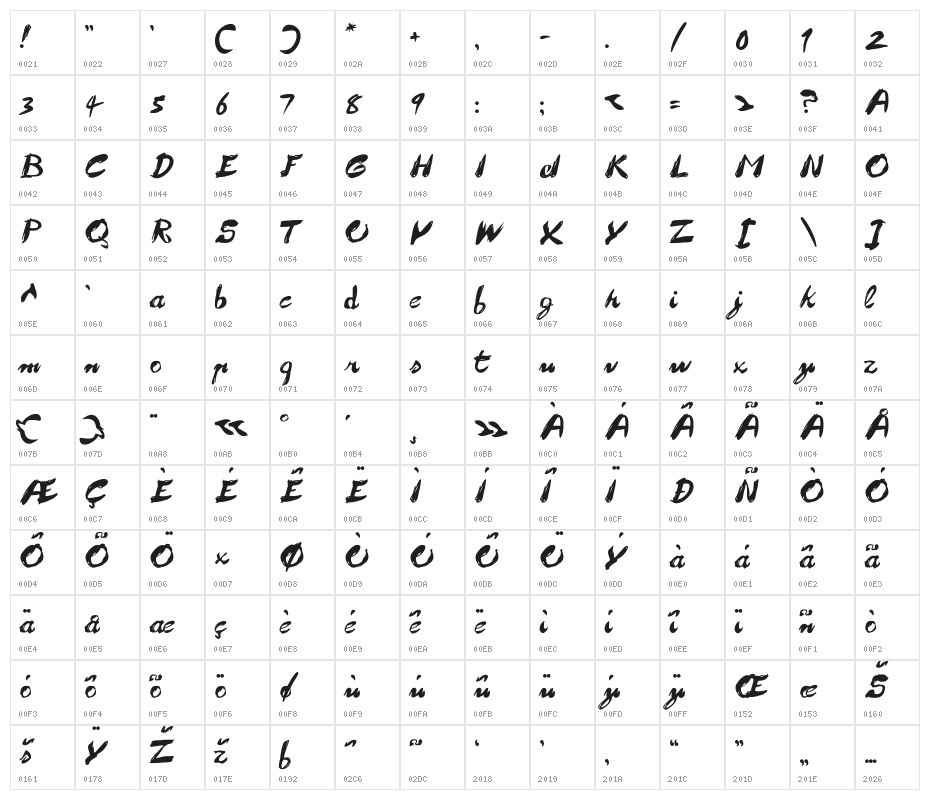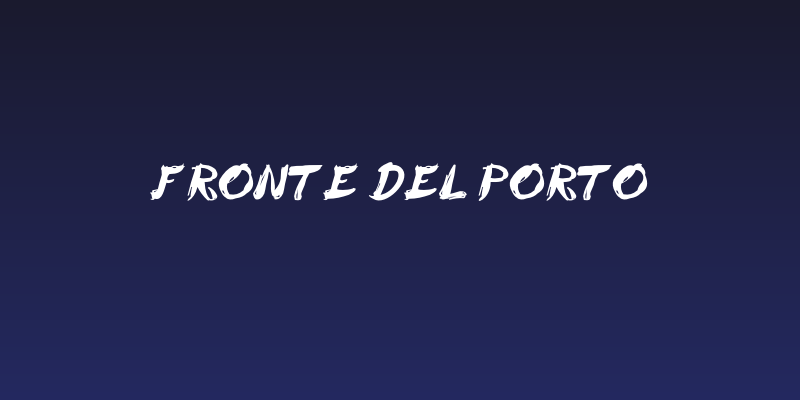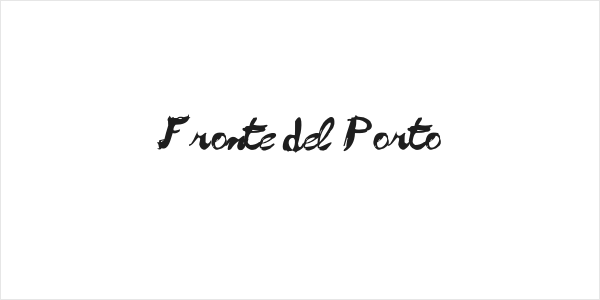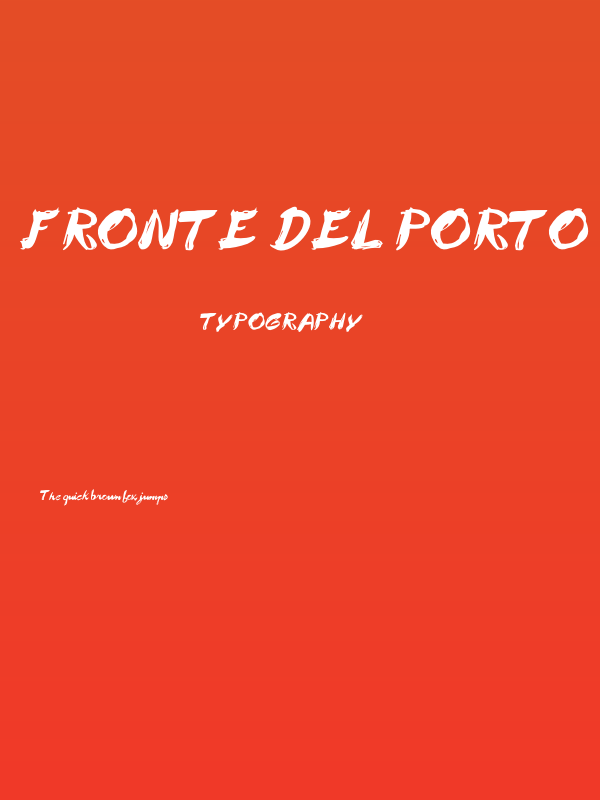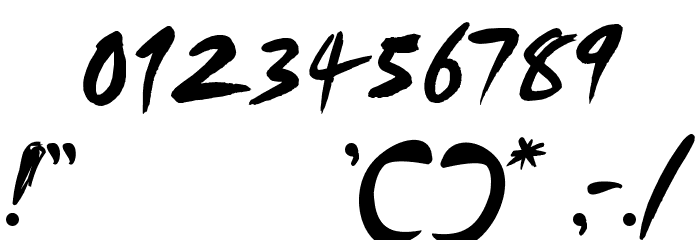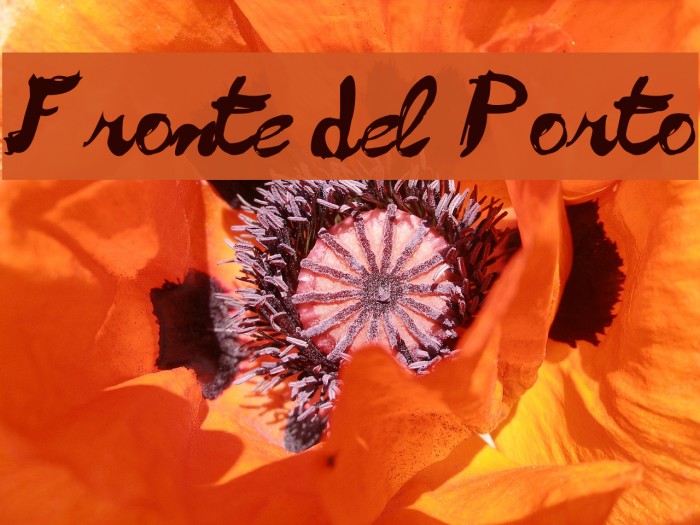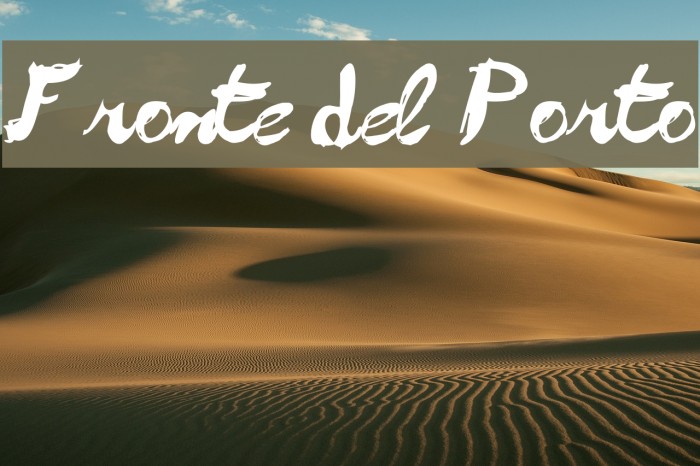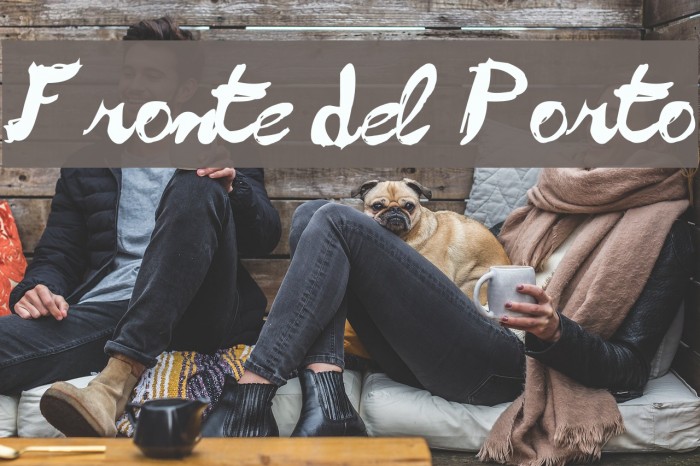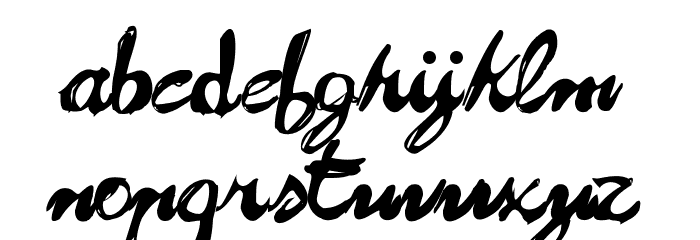
Fronte del Porto Font
| Caso d'uso | Logos, Headlines, Artistic projects |
| Progetti proposti | Ideal for branding, invitations, greeting cards, and artistic projects that require a personal and creative touch. |